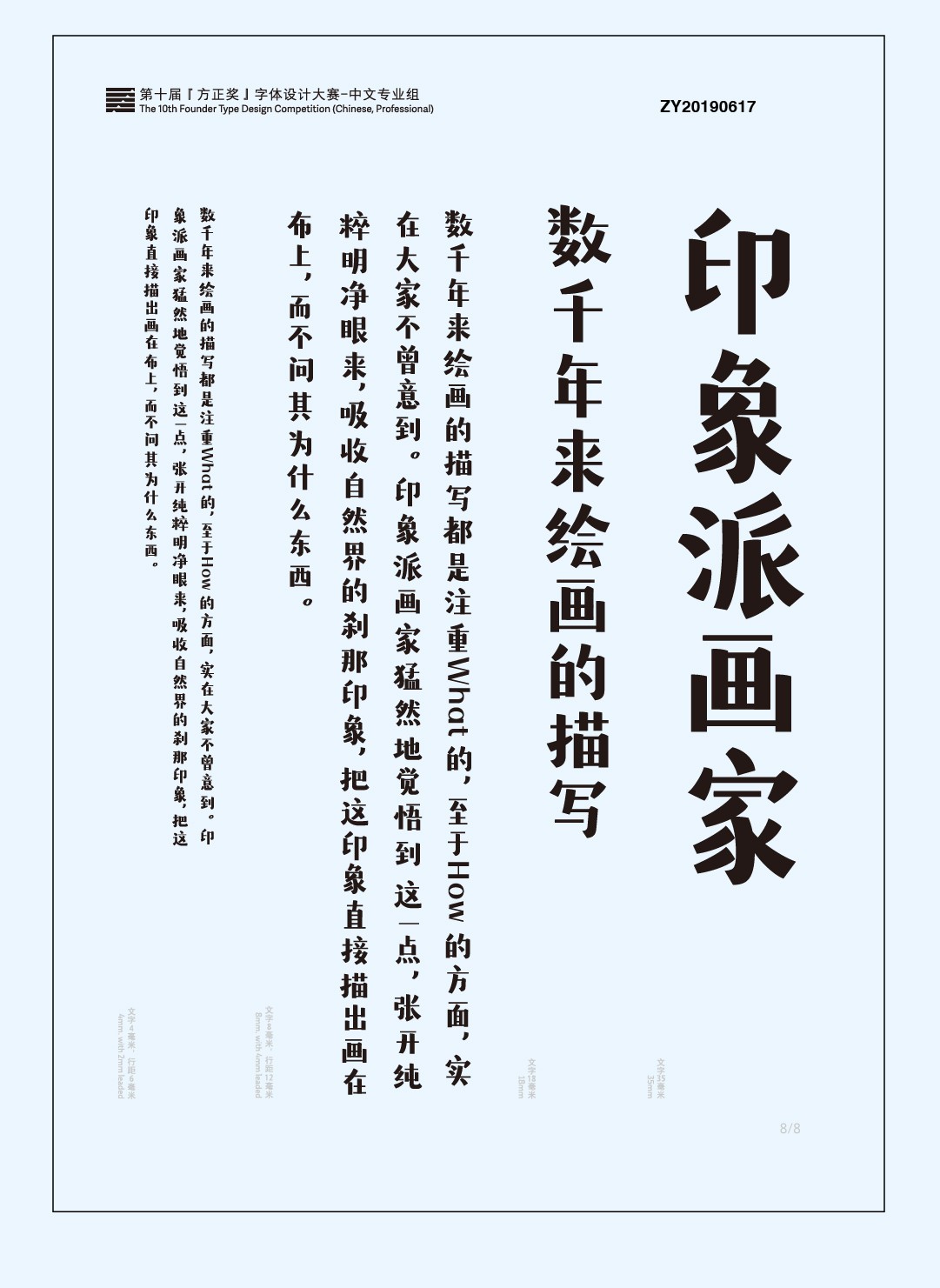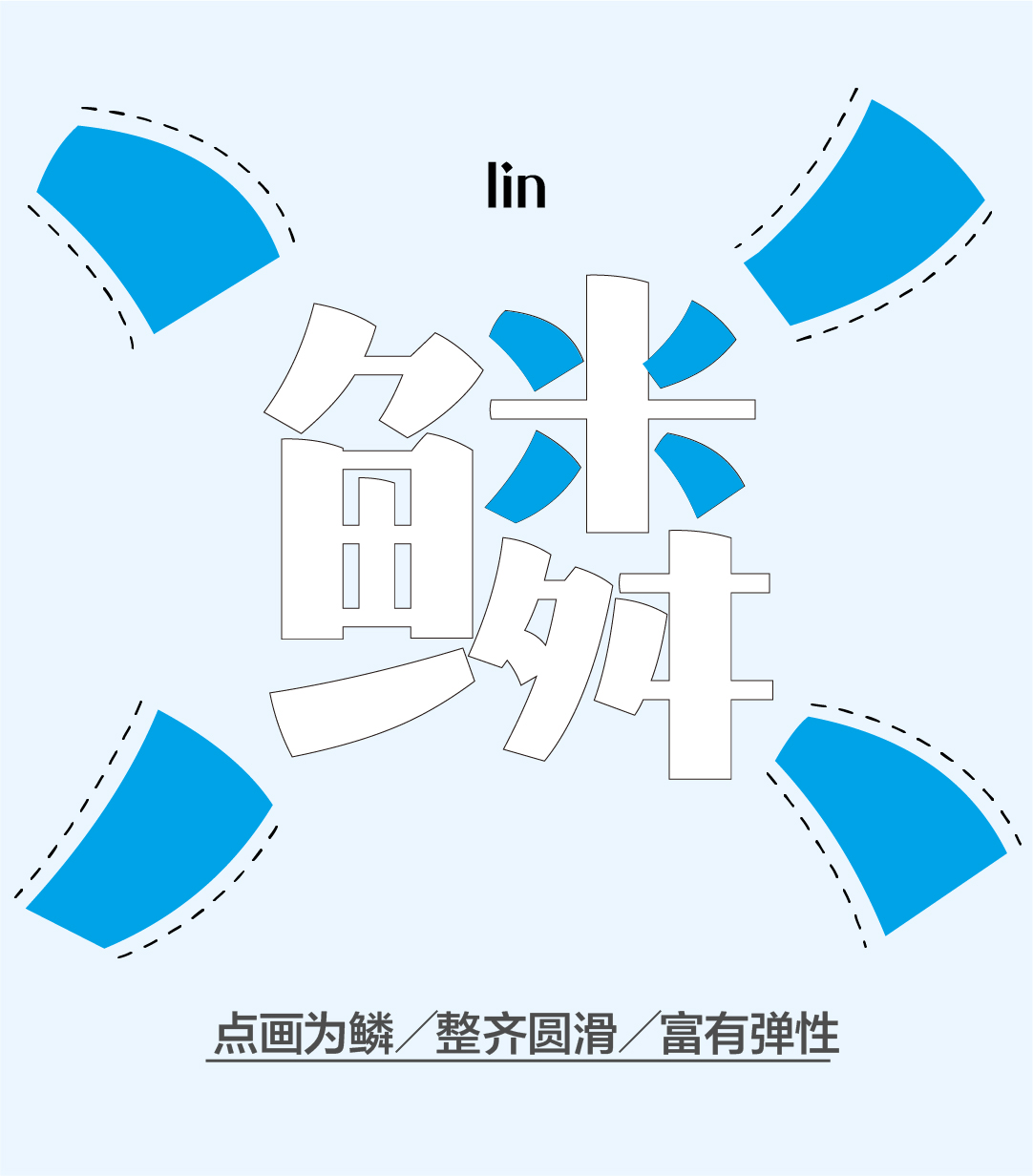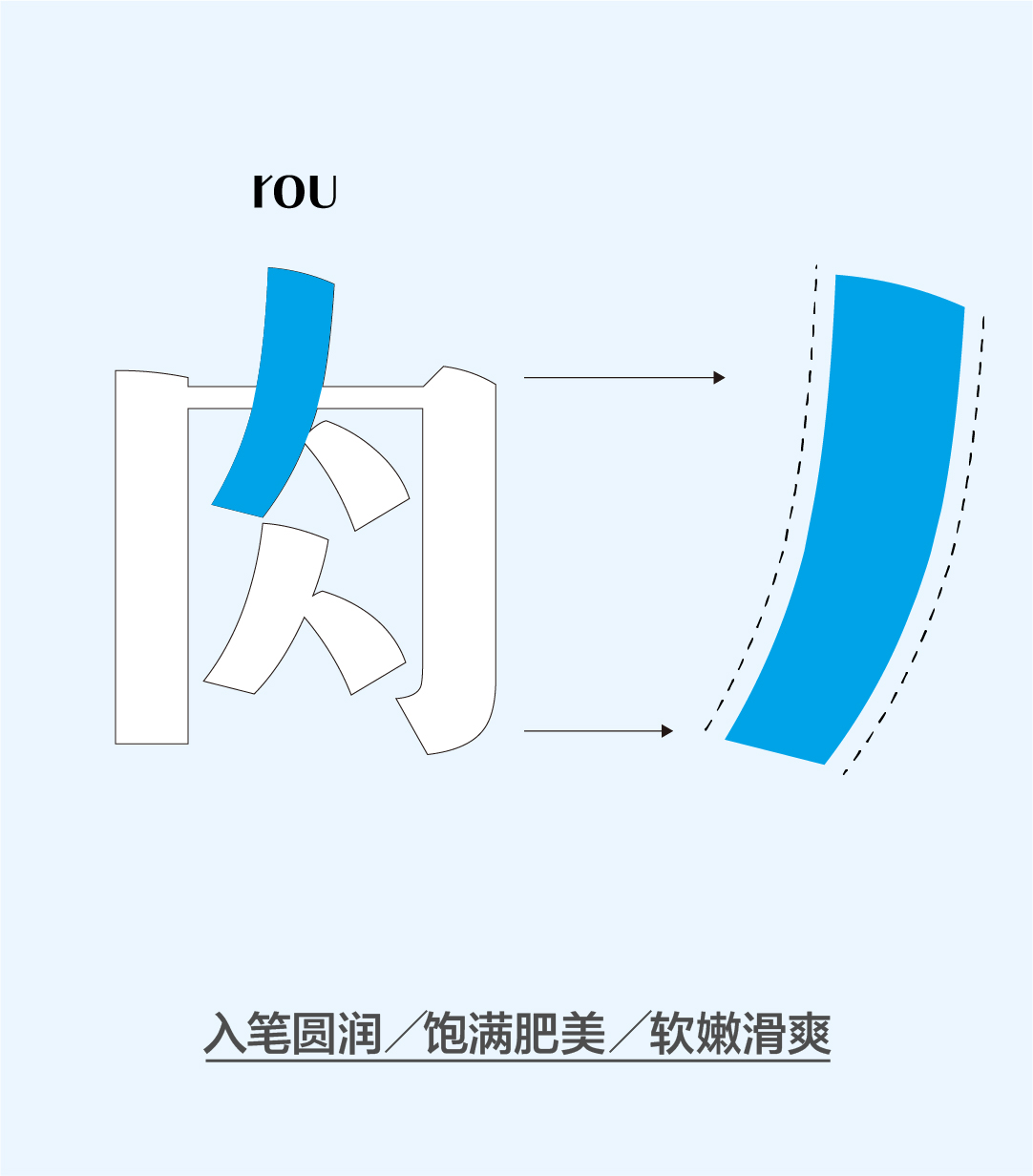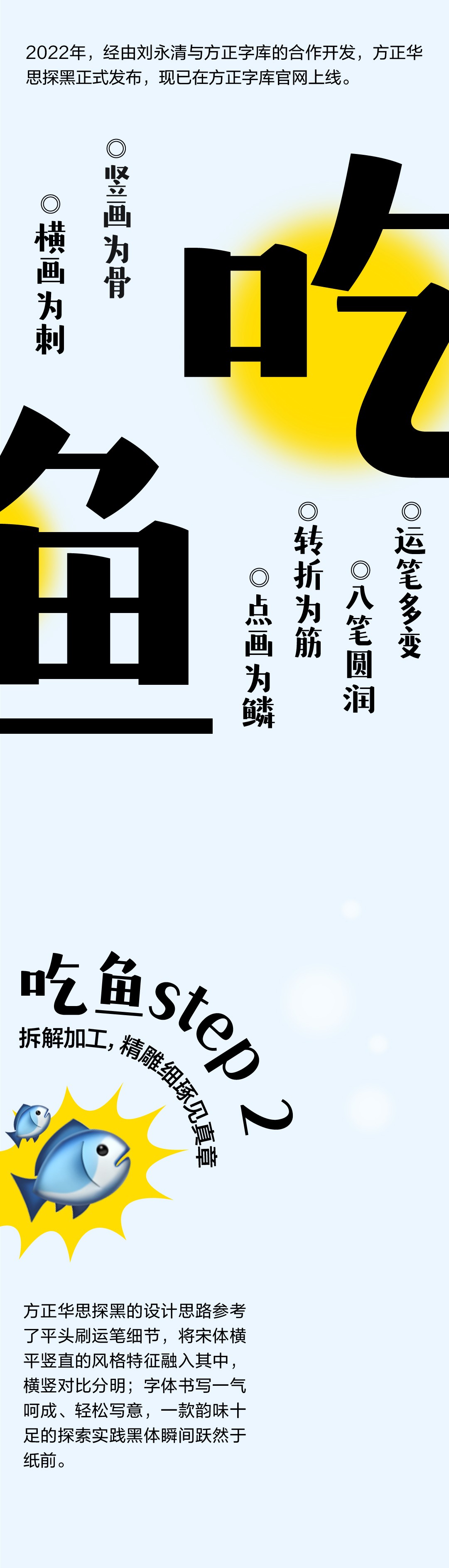
方正华思探黑
方正华思探黑,这款字体结构工整、笔画清晰,兼顾美观与易读性,适用于标题、正文、海报、包装、LOGO 等多种场景。字形优雅稳定,风格百搭耐看,适配日常排版与创意设计,让文字呈现更舒适、更具质感。方正华思探黑一笔一画,皆是细节,以均衡的比例、流畅的线条打造舒适视觉体验,字形端正大气,风格简约现代。无论是商业设计、品牌宣传还是日常排版,都能轻松驾驭,让文字更有格调与力量。方正华思探黑字体下载。
华思探黑为第十届方正奖参赛作品。这是一款在实际商业设计中探索实践出来的字体,其特征是要有强烈的视觉冲击力,又要有清晰端庄方正的架构特征,同时还不能象黑体那样呆板,也不能象一些童体那样过于活泼,基于上述特点,在设计时试想手拿一把平头刷子,把宋体的横平竖直的端庄特征用于其中,平刷圆润入笔,运笔时整体横画较细,保持文字的筋骨;点撇捺时由于平头刷的手握姿势使得黑体粗壮有力的风格巧妙融入其中,由圆润入笔,运笔力度由大到小,提笔方点收笔、平直,一气呵成,一款韵味十足的探索实践黑体瞬间跃然于纸前,从运笔及笔画的变化,把轻松、变化,且相对规范的新黑体风貌淋漓尽致展现了出来,字体架构从心所欲,轻松自如,横平竖直的特征所得字体再怎么变化都保持着一股端庄方正、文雅而又不失活泼时尚气息,字体风格平实,简洁有力,视觉冲击力极强,是一款在商业推广应用中极好使用的字体。